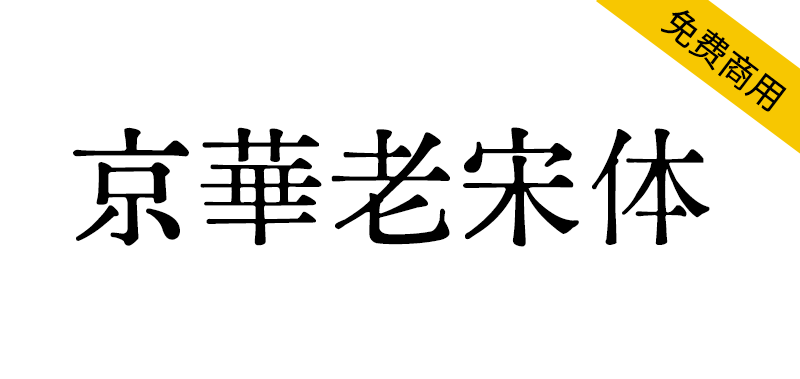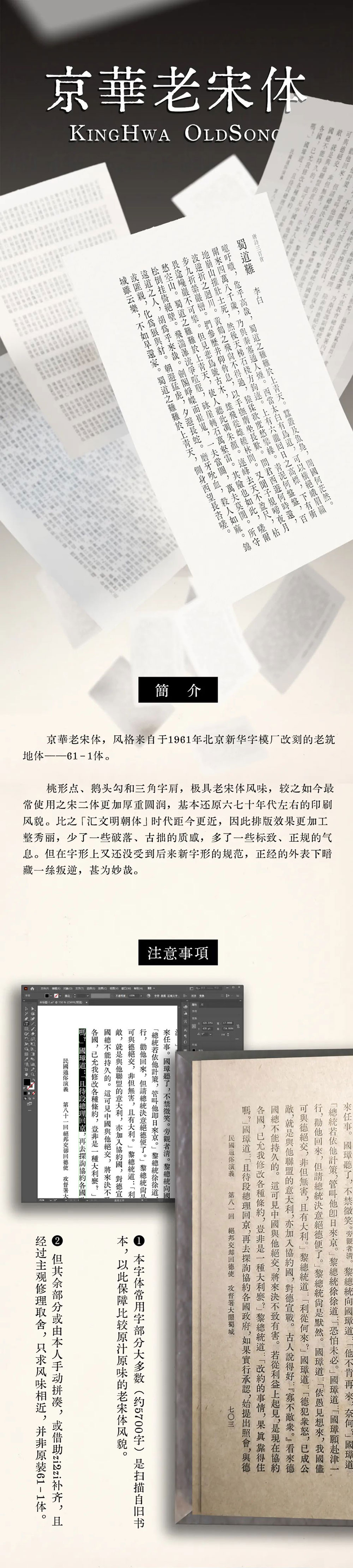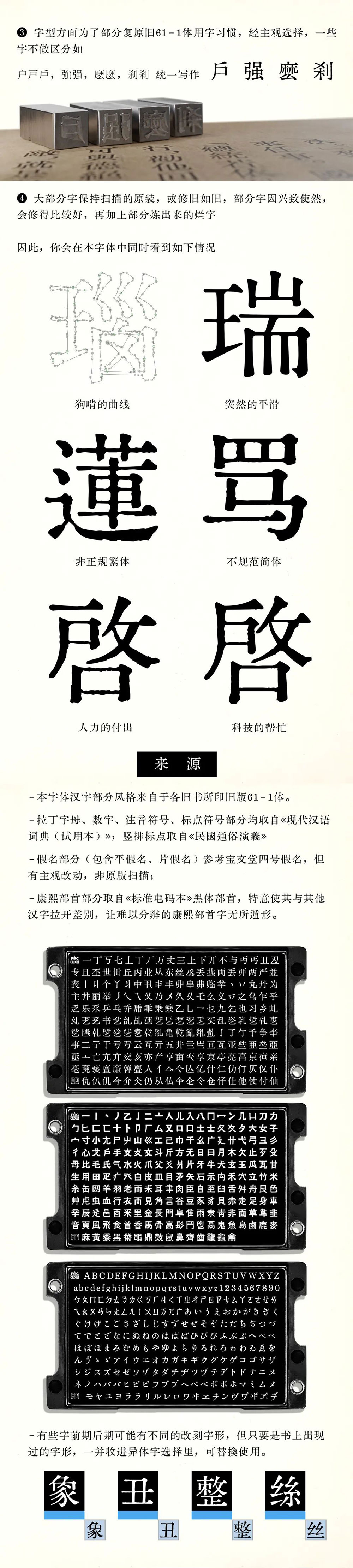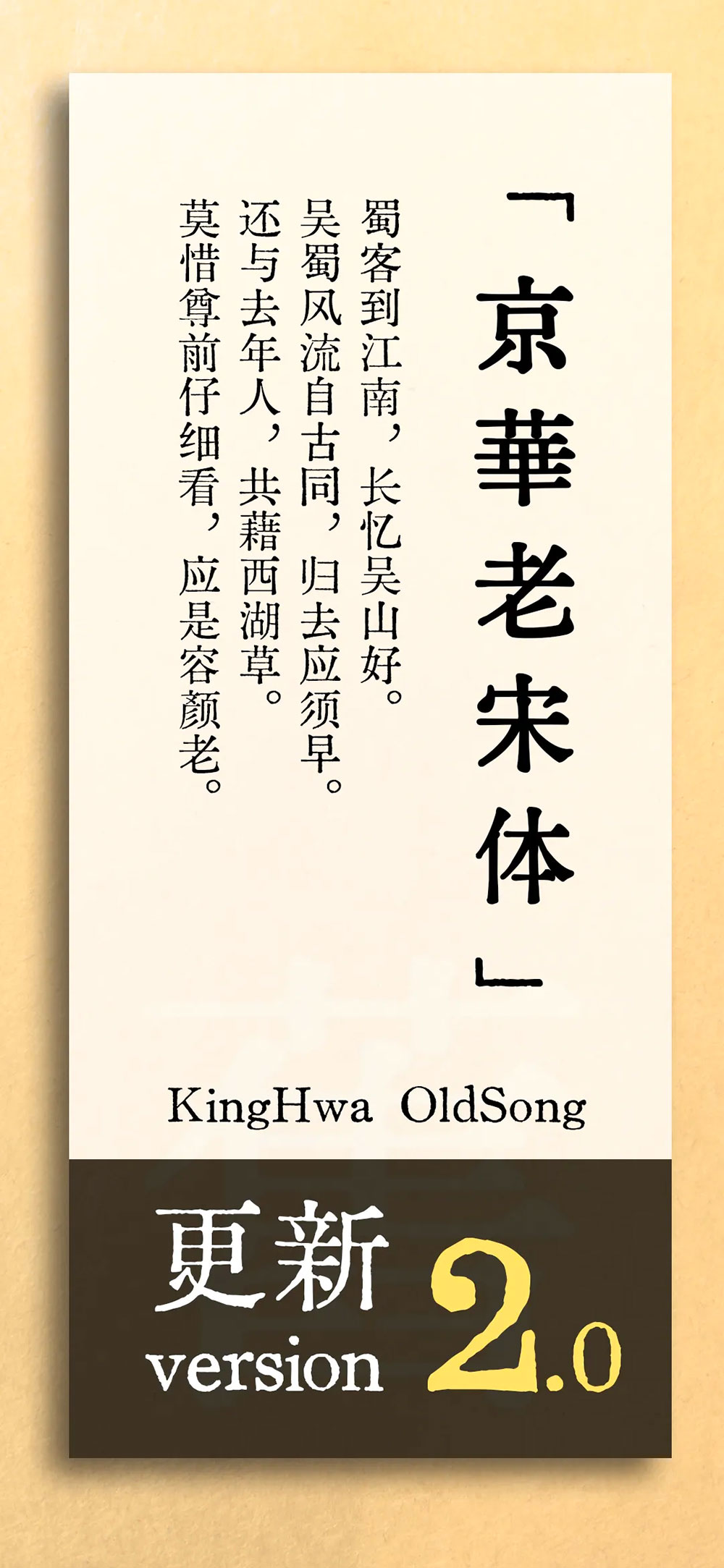
京华老宋体(京華老宋体),风格来自1961年北京新华字模厂改刻的老筑地体——61-1体。桃形点、鹅头勾和三角字肩,极具老宋体风味,较之如今最常使用之宋二体更加厚重圆润,基本还原六七十年代左右的印刷风貌。比之「汇文明朝体」时代距今更近,因此排版效果更加工整秀丽,少了一些破落、古拙的质感,多了一些标致、正规的气息。但在字形上又还没受到后来新字形的规范,正经的外表下暗藏一丝叛逆,甚为妙哉。
注意1:本字体常用字部分大多数(约5700字)是扫描自旧书本,已此保障比较原汁原味的老宋体风貌。
注意2:但其余部分或者由本人手动拼凑,或借助zi2zi补齐,且经过主观修理取舍,只求风味相近,并非原装61-1体。
注意3:字型方面为了部分复原旧61-1体用字习惯,经主观选择,一些字不做区分。
注意4:大部分字保持扫描的原装,或修旧如旧,部分字因兴致使然,会修得比较好,再加上部分炼出来的烂字。因此,你会在本字体中同时看到:狗啃的曲线、突然平滑、非正规繁体、不规范简体、人力的付出、科技的帮忙。
京華老宋体2.0更新内容:1.修复错讹字形若干、2.区分分码字、3.新增【样式集1】【簡】60年代用字及字形、4.新增【样式集2】【日】日本新字形、5.新增【样式集3】【原】61-1体原版用字及字形、6.新增【样式集4】【古】古籍印刷通用字規範字形、7.新增【样式集5】【居中標點】。